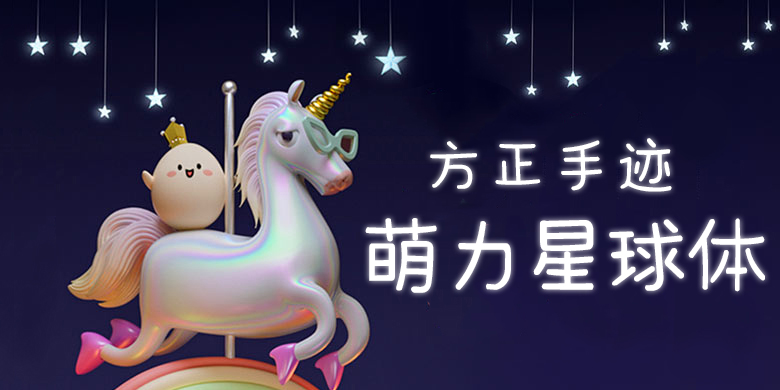
方正手迹-萌力星球体 品牌: 方正手迹 设计师: 厦门萌力星球网络有限公司 发行时间:2020 字库编码:大陆简体(GB2312-80) 分类:创意书写 字体属性:心动字 创意卡通有趣创意书写标题杂志书籍广告影视电商海报包装新媒体综艺游戏动漫 萌的种类也很多种,萌力星球是属于那种偏向于男孩子的萌,稚拙无华,呆萌可爱。字体线条简洁精致,字形方正,字面较大,具有良好的阅读显示效果。适用于少儿类书刊,及现代诗歌、短文的排版以及文化、商业类品牌的广告语设计。 字体下载地址 官方下载